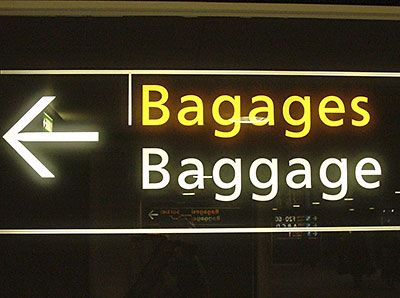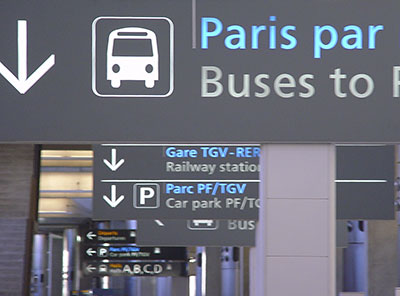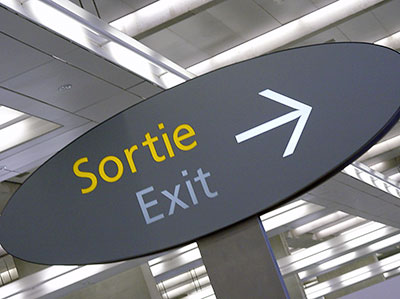
Frutiger: Inbegriff der LesbarkeitMitte der 60er Jahre begann die Planung für den Pariser Flughafen
Charles de Gaulle. Die Entwicklung des Leitsystems wurde Adrian Frutiger
übertragen. »Alle dachten, ich würde zur Univers greifen. Doch
sie ist ungeeignet für die schnelle Wahrnehmung.« erinnerte er sich an
![]() Frutiger ist ein Designklassiker. Man sieht ihr das Alter nicht an.
Offiziell wurde sie 1969 geboren. Wer sich erinnert, welche Designsymptome die
Hippie-Zeit prägten – Glockensaum, florale Muster, schrille
Farben –, wird bestätigen: zum Glück sieht man Frutiger ihre
Herkunft nicht an. Andere Schriften dieser Zeit, wie ITC Avant Garde, Aachen, Revue oder Serpentine, sind klar von einer Seventies-Optik
geprägt. Das schränkt Neutralität und damit Einsatzvielfalt
ein.
![]() Frutiger auf dem Flughafen Charles De Gaulle im Jahre 2001 Möglicherweise liegt die Ursache für Frutigers Zeitlosigkeit auch darin, dass der Grundstein für die Schriftfamilie bereits 1959 gelegt wurde. Bei der französischen Gießerei Sofratype entwickelte Adrian Frutiger zusammen mit André Gürtler für die Zeilengussmaschine eine Sansserif namens Concorde, nicht zu verwechseln mit der Times-Alternative gleichen Namens, die Günter Gerhard Lange für die H. Berthold AG schuf. Als Linotype Mitte der 60er Jahren die Pariser Sofratype übernahm, wurde Concorde eingestellt, die Urheberrechte gingen an die Entwerfer zurück. ![]() Entwürfe zur Sans-Serif Concorde von Adrian Frutiger und André Gürtler aus dem Jahr 1959 (Abbildung: Linotype) Mitte der 60er Jahre begannen auch die Planungen für den Pariser Großflughafen Roissy Charles de Gaulle. Der junge Architekt Paul Andreu rief ein Expertenkommission aus Farbpsychologen, Philosophen, Musikern und Designern zusammen, um in Roissy wegweisende Neuerungen einzuführen. Die Entwicklung des Leitsystems wurde dem Büro Adrian Frutigers übertragen. »Alle dachten, ich würde zur Univers greifen. Doch mir wurde schnell klar, dass sie zu rund und geschlossen für die schnelle Wahrnehmung von Wegweisern war. Ich nahm mir die Zeichnungen für die Concorde vor und machte ein paar Skizzen.« So erinnerte sich Frutiger an die Geburtsstunde seiner berühmtesten Schrift. (vergl.: Linotype Font-Feature Adrian Frutiger – Traces) ![]() Für die schnelle Wahrnehmung der Wegweiser – auch im Reisestress – entwickelte Adrian Frutiger eine offene Schrift mit unverwechselbaren Zeichenformen Die Idee einer »Flughafenschrift« begeisterte Paul Andreu und die gesamte Fachwelt. Die Ergebnisse waren überzeugend, im wahrsten Wortsinn wegweisend. Da ist es nur verständlich, dass in den folgenden Jahren die Nachfrage nach der Roissy-Schrift stetig zunahm. Typografen in aller Welt wollten sie nicht nur für Schildersysteme einsetzen, sondern auch für Drucksachen. Denn: eine Schrift, die auf Wegweisern gut lesbar ist, wird die gleiche Eigenschaft auch im Druck entfalten. 1977 brachten die D. Stempel AG und Linotype die Schrift, ausgebaut zu einer kleinen Familie, auf den Markt. Sie wurde rasch zum Bestseller und mehrfach erweitert. Nach wenigen Jahren wurde Frutiger zum Inbegriff für Lesbarkeit. Ihre Konstruktion ist weder streng geometrisch, noch humanistisch. Maßstab für die Gestaltung eines jeden Buchstabens ist seine rasche Erkennbarkeit und die Unterscheidbarkeit von verwandten Lettern. Die Genialität Adrian Frutigers bei der Entwicklung seiner Schrift lag in der Fähigkeit, Wahrnehmungs- und Konstruktionsprinzipien so gegeneinander abzuwägen, dass sich ein Zeichensatz mit maximale Lesbarkeit ergab. ![]() Egal ob Auflicht oder Hinterleuchtung: Die Zeichen der Frutiger bleiben auch bei Überstrahlung stets gut wahrnehmbar Nachdem die Schrift rund 30 Jahre ihren Dienst auf dem Airport Charles De Gaulle getan hatte, unterzog ihr Schöpfer sie im Jahre 1998 bei einem Besuch in Paris einer kritischen Betrachtung: »Ich glaube, dass die Roissy-Schrift ein wenig zu leicht und zu eng spationiert eingesetzt wird: zu viel Enge um die Buchstaben.« Auch mit der PostScript-Version war Frutiger nie richtig glücklich. Ihr Ausbau ist durch Brüche gekennzeichnet und die Strichstärke der Regular war ihm stets zu kräftig. Die Überarbeitung seiner 59 Univers-Schnitte im Jahre 1999 gab ihm ausreichend Auftrieb, ein Redesign seiner Frutiger in Angriff zu nehmen. ![]() Einer der größten Schriftentwerfer unserer Zeit: Adrian Frutiger, Interlaken, Schweiz, 2004 Rund zwei Jahren nahmen sich der Urheber und der freie Schriftentwerfer Erik Faulhaber Zeit, die Original-Frutiger komplett zu renovieren. Alle Zeichen wurden neu digitalisiert, wobei die Buchstabenformen kaum angetastet wurden. Lediglich das ß und das et-Zeichens sind völlig neu, das s und das t erfuhren ein dezentes Facelifting. Die Strichstärkenabstimmung erfolgte in 6 statt in 5 Stufen, wobei man nicht mathematisch linear vorging, sondern nach optischen Kriterien. So wurden die fetten Schnitte prägnanter, der Grundschnitt leichter. Hintergründe zum Redesign verriet Faulhaber im Dezember 2004 dem Typeforum. Bei den Kursiven sprang Frutiger über seinen Schatten – oder wurde er geschubst? Die Fachwelt kennt seine Vorliebe für technisch schräg gestellte Sansserifs, die er auch bei der Überarbeitung der Univers durchgesetzt hatte. Doch bei der Frutiger Next ließ er sich zu einer klassischen Kursiven überreden, mit eigenen Formen für a, g und f. Keine Frage: der Frutiger Next steht dieses Ideal einer Kursiven ausgezeichnet. Herausgegeben: Mi - August 24, 2005 at 05:22 nachm. | |